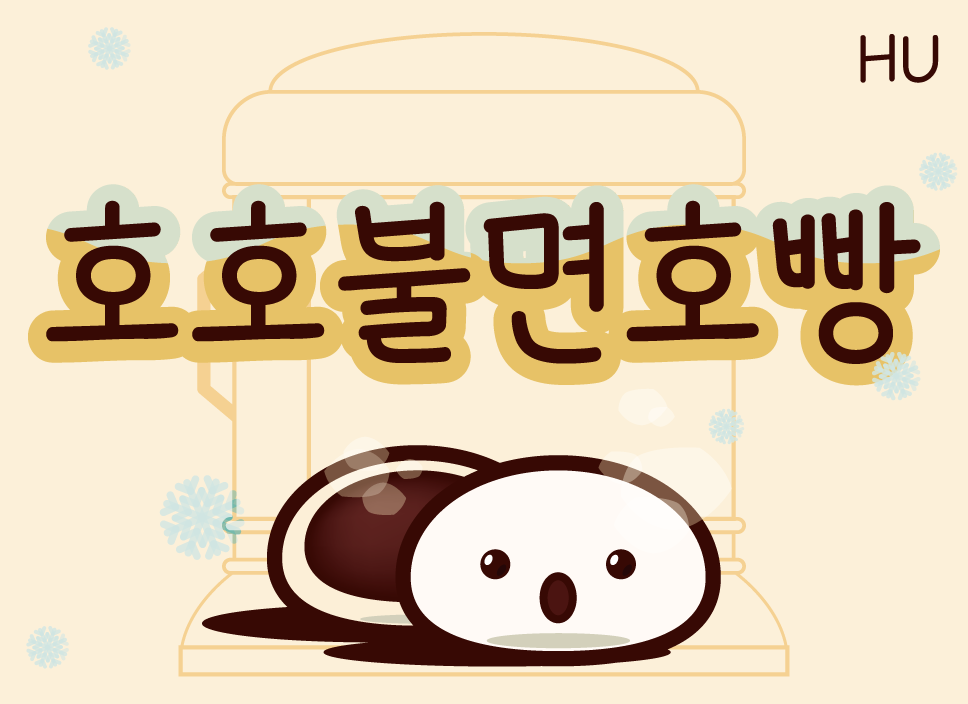
펜으로 쓴 것과 같은 무심하게 툭 삐져나온 획과 둥근 모서리가 특징인 손글씨입니다.
*자소크기는 보통이며, 굵기는 미디움으로 분류됩니다.
펜으로 쓴 것과 같은 무심하게 툭 삐져나온 획과 둥근 모서리가 특징인 손글씨입니다.
*자소크기는 보통이며, 굵기는 미디움으로 분류됩니다.